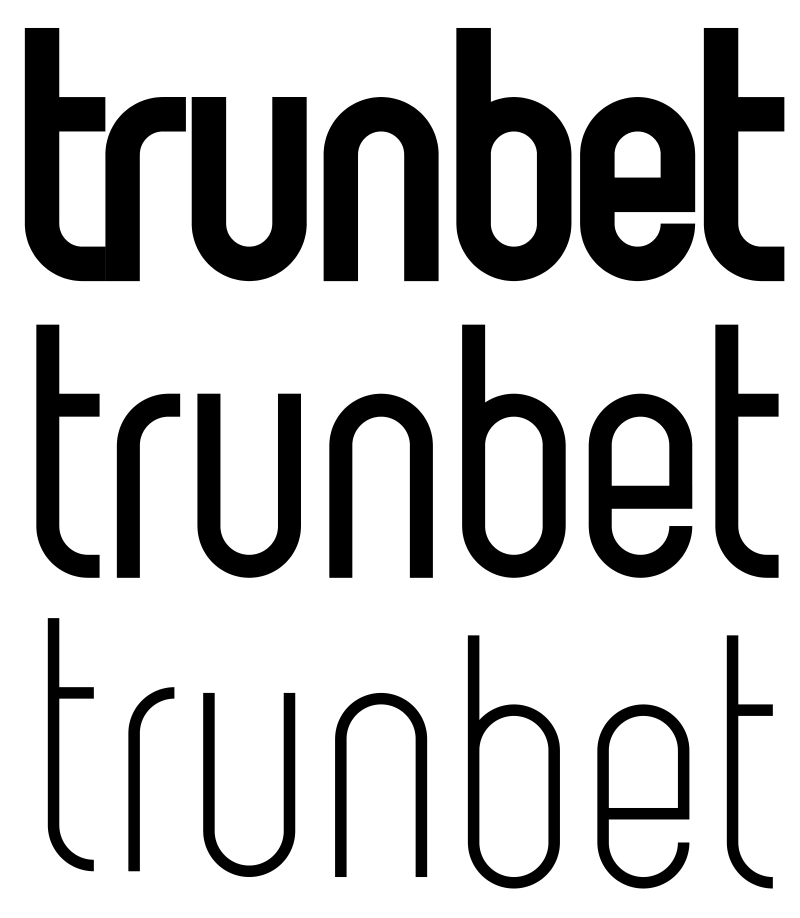
Tipografía Trescirc – Parte 1
Con motivo del cambio del nombre del blog, me puse a buscar alguna tipografía con características que tenía en mente. Empecé a hacer combinaciones con la Futura condensada y la Lacuna. Tomé características que me gustaban de ambas tipografías y así surgió la tipografía que ven arriba. Estoy diseñando el alfabeto completo con variables de peso y proporción, mayúsculas y minúsculas.
El objetivo también es poner en práctica cuestiones que he aprendido en estos años sobre tipografía.